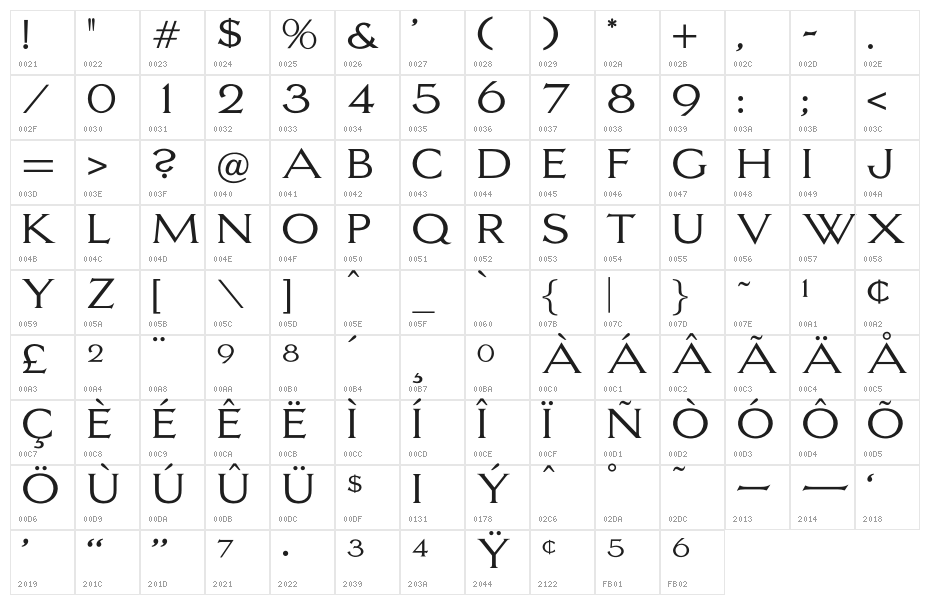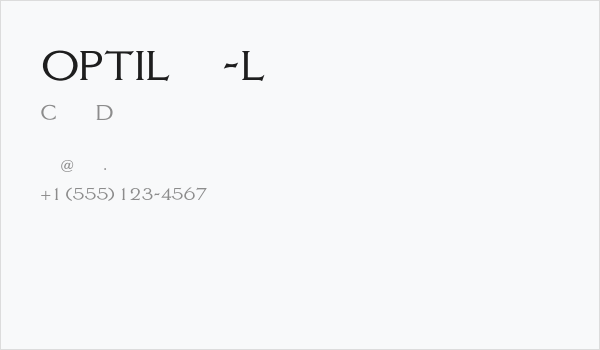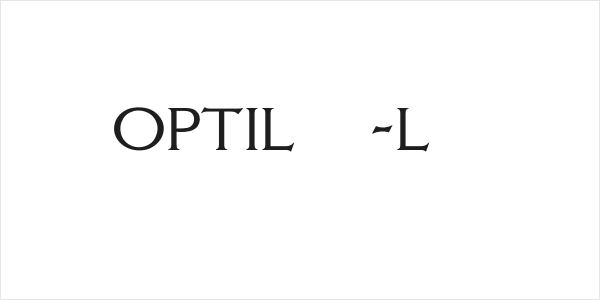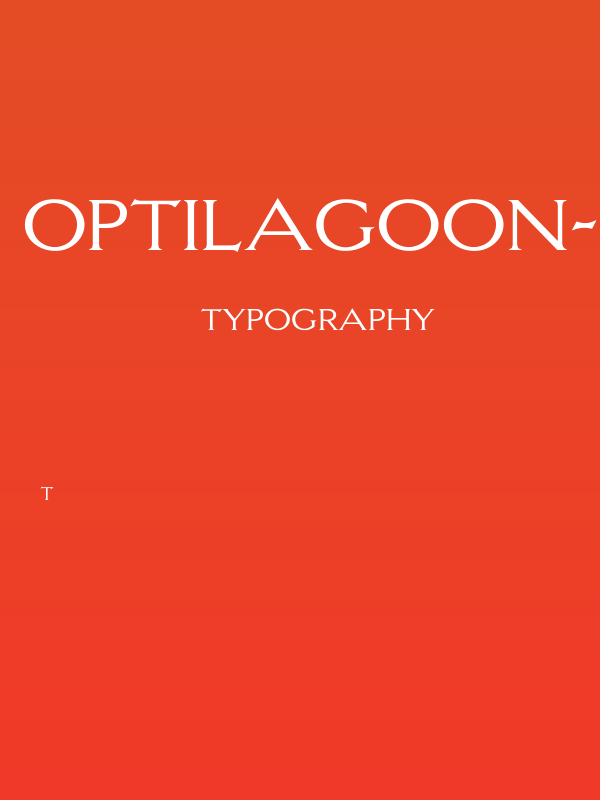
OPTILagoon-Light Font
| Kategorien | Serif |
| Gesamtstil | Classic |
| Anwendungsfall | Headlines, Body text, Logos |
| Vorgeschlagene Projekte | Ideal for editorial design, book covers, formal invitations, and branding projects that require a touch of elegance. |